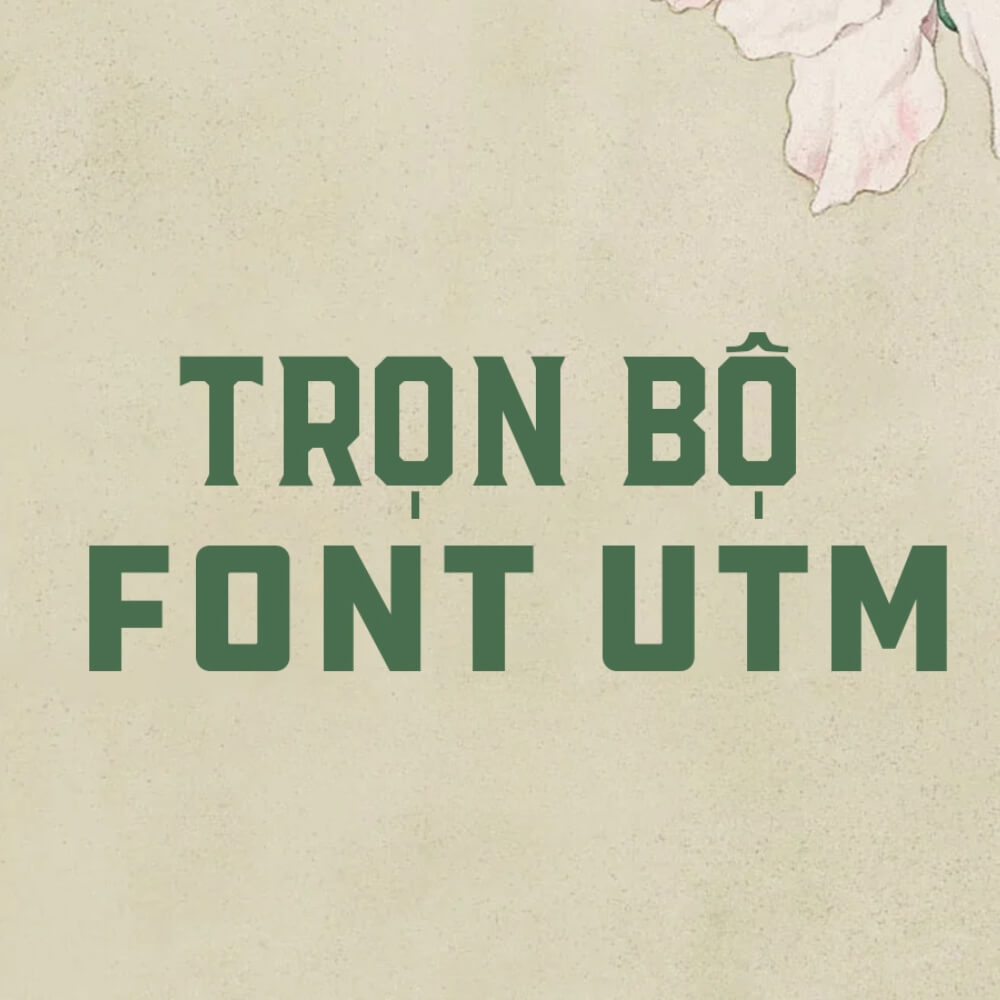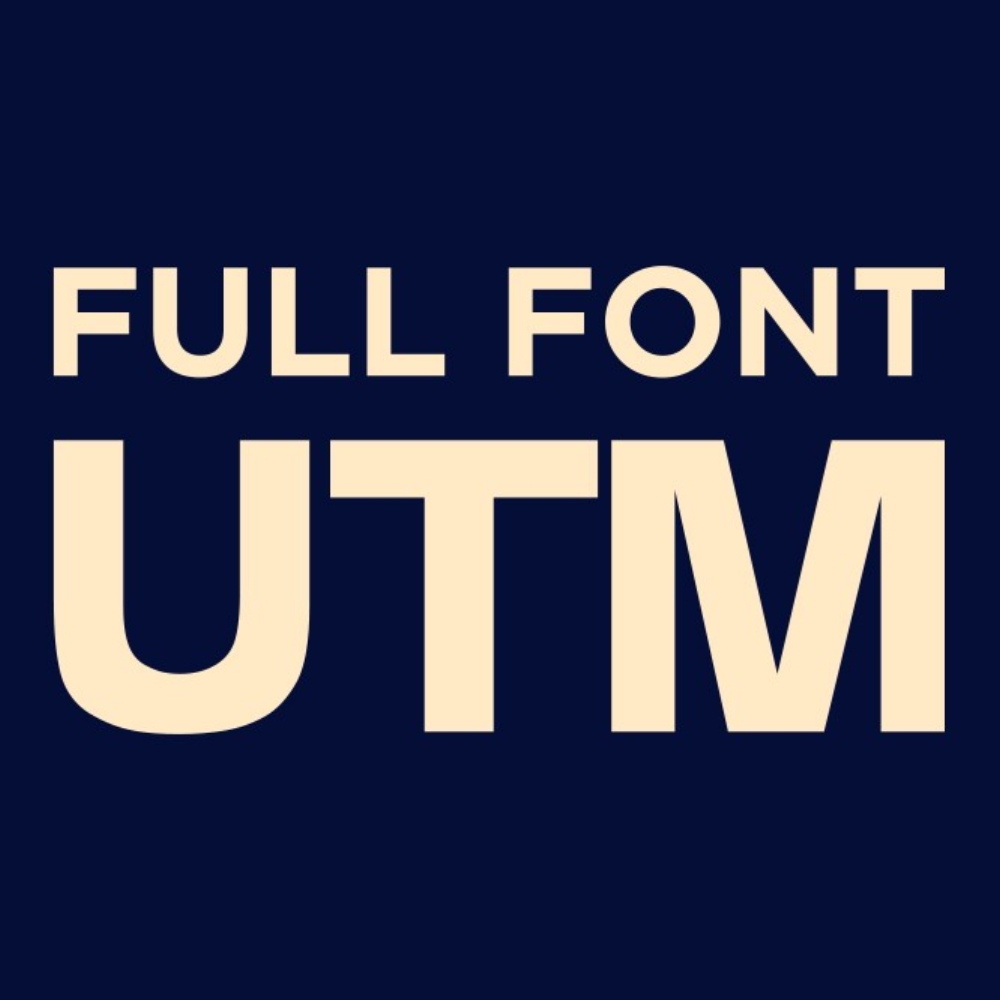
Tải font UTM đầy đủ – bộ font chữ phổ biến nhất tại Việt Nam với hàng trăm phiên bản việt hóa từ các font nổi tiếng thế giới. Font UTM được sử dụng rộng rãi trong thiết kế bao bì sản phẩm, túi giấy, catalogue và in ấn thương mại nhờ sự đa dạng phong cách và khả năng hiển thị tiếng Việt hoàn hảo.
Bộ font UTM là gì?
Bộ font UTM (viết tắt của University of Transport and Communications – Đại học Giao thông Vận tải Hà Nội) là bộ font được việt hóa từ các font chữ nổi tiếng thế giới. Bộ font này ra đời với mục đích ban đầu là phục vụ giảng dạy và nghiên cứu, nhưng sau đó được sử dụng rộng rãi trong cộng đồng thiết kế Việt Nam nhờ khả năng hỗ trợ tiếng Việt đầy đủ dấu thanh.
Bộ font UTM bao gồm hàng trăm font được việt hóa từ các font gốc nổi tiếng như Helvetica (thành UTM Helvetins), Bebas (thành UTM Bebas), Impact (thành UTM Impact), Avo (thành UTM Avo), và nhiều font khác. Mỗi font UTM thường có từ 2-4 phiên bản với độ dày khác nhau (Regular, Bold, Italic, Bold Italic).
Ưu điểm lớn nhất của bộ font UTM là hỗ trợ đầy đủ ký tự tiếng Việt với tất cả dấu thanh (á, à, ả, ã, ạ, ă, ắ, ằ…), trong khi nhiều font gốc không hỗ trợ hoặc hỗ trợ kém tiếng Việt. Điều này giúp designer Việt Nam dễ dàng sử dụng các font đẹp mà không lo lỗi font.
Một số font UTM phổ biến nhất:
• UTM Helvetins: Việt hóa từ Helvetica, font sans-serif cổ điển, phù hợp mọi ngành hàng.
• UTM Bebas: Việt hóa từ Bebas Neue, font condensed mạnh mẽ, hiện đại.
• UTM Impact: Việt hóa từ Impact, font đậm nổi bật cho poster, billboard.
• UTM Swiss 721 Black Condensed: Font condensed cực đậm, tạo hiệu ứng thị giác mạnh.
• UTM Neo Sans Intel: Font hiện đại, công nghệ, phù hợp ngành IT.
• UTM Neutra: Font geometric thanh lịch, cao cấp.
• UTM Thư Pháp Thiên Ân: Font thư pháp Việt Nam, phong cách truyền thống.
• UTM Aristote: Font serif cổ điển, trang trọng.
• UTM Avo: Font sans-serif hiện đại, minimalist.
Download font UTM Neo Sans Intel mang phong cách tối giản, phù hợp thiết kế công nghệ
Bộ font UTM Việt hóa là một trong những bộ font phổ biến và được sử dụng rộng rãi trong thiết kế, văn phòng và in ấn nhờ khả năng hiển thị tiếng Việt chuẩn, dễ đọc và đa dạng phong cách. Từ các font thanh lịch, hiện đại đến cổ điển, sáng tạo, UTM đáp ứng tốt nhiều nhu cầu sử dụng khác nhau.
Tên font UTM
Phong cách
Ứng dụng in ấn tốt nhất
UTM Helvetins
Sans-serif cổ điển, trung tính. Bao bì mọi ngành, catalogue, brochure đa dụng.
UTM Bebas
Condensed mạnh mẽ, hiện đại. Logo thương hiệu năng động, poster thể thao.
UTM Impact
Sans-serif cực đậm, nổi bật. Tải font UTM Impact về dùng cho poster quảng cáo, billboard, standee sự kiện.
UTM Swiss 721 Black Condensed
Condensed cực đậm, hiệu ứng mạnh. Tiêu đề chính túi giấy, hộp quà cao cấp.
UTM Neo Sans Intel
Hiện đại, công nghệ, futuristic. Bao bì sản phẩm công nghệ, điện tử, IT.
UTM Neutra
Geometric thanh lịch, cao cấp. Bao bì mỹ phẩm, thời trang, lifestyle.
UTM Thư Pháp Thiên Ân
Thư pháp Việt Nam truyền thống. Thiệp Tết, liễn xuân, quà tặng văn hóa.
UTM Aristote
Serif cổ điển, trang trọng. Catalogue cao cấp, sách, tài liệu chuyên nghiệp.
UTM Avo
Sans-serif hiện đại, minimalist. Logo startup, bao bì sản phẩm organic.
Ứng dụng font UTM trong thiết kế bao bì và in ấn
Bộ font UTM với sự đa dạng phong cách được ưa chuộng trong ngành thiết kế Việt Nam:
• Hỗ trợ tiếng Việt hoàn hảo: Đây là lý do chính khiến designer Việt ưa chuộng UTM. Tất cả dấu thanh tiếng Việt đều hiển thị chuẩn, không bị lỗi font hay thiếu ký tự.
• Đa dạng phong cách: Từ sans-serif hiện đại (UTM Helvetins, UTM Avo), condensed mạnh mẽ (UTM Bebas, UTM Swiss 721), đến thư pháp truyền thống (UTM Thư Pháp Thiên Ân) – bộ UTM có font cho mọi nhu cầu thiết kế.